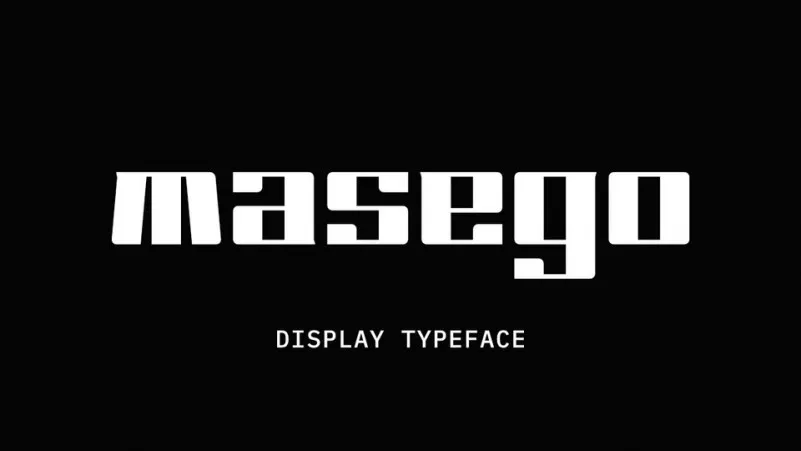
A Masego Display Font é uma tipografia geométrica e retangular com canto angulado. Feita pelo designer Adebowale Adegoke, ela se encaixa na categoria das fuentes de exibição com linhas afiadas. Com um design que remete à simplicidade da geometria moderna, a Masego oferece uma aparência elegante e clean para qualquer projeto onde desejar destacar o estilo ou usar letras digitais. Seja para criar logotipos memoráveis, artes de mídia social impactantes ou até mesmo porções em editoriais, a Masego Display é um recurso gráfico que traz uma nova dimensão ao seu design digital.